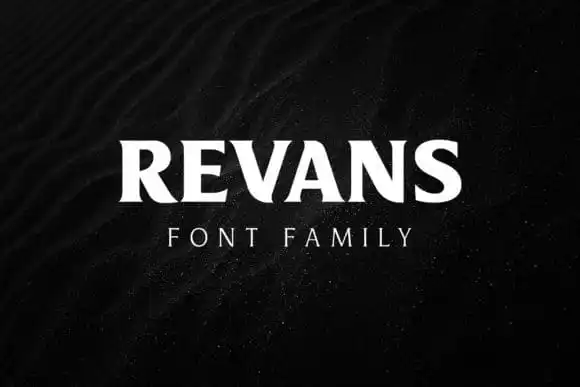
Revans Serif é uma fonte serif que inspira-se nos anos 19, oferecendo um estilo moderno com um toque memorável e elegante. Desenvolvida pela sartstudio, esta font é cuidadosamente projetada para apresentar uma aparência sólida, luxuosa e refinada. Seja você um designer que busca uma fonte robusta ou estilizada, Revans Serif é uma escolha segura para se juntar ao seu design. Com a sua beleza minimalista mas sofisticada, Revans será certamente uma opção elegante para qualquer projeto gráfico. Ideal tanto para o design de revistas quanto para aplicativos móveis, esta fonte é a escolha perfeita para quem busca um equilíbrio entre elegância e modernidade. A sartstudio leva a sério em garantir que cada detalhe da Revans seja cuidadosamente projetado, tornando-a uma opção confiável para qualquer designer gráfico.